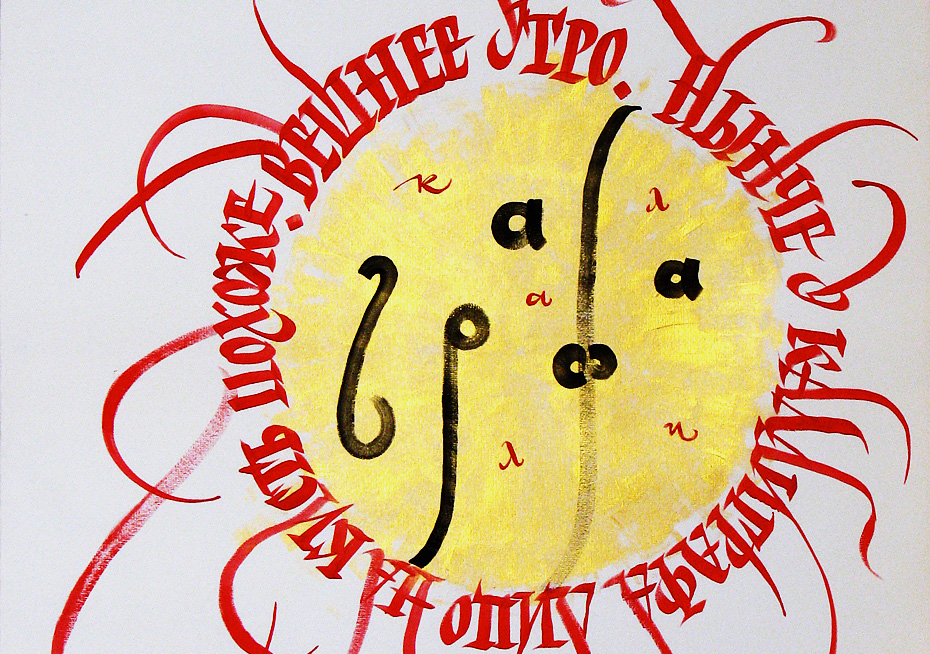
Соло шрифта Amalta
Шрифт Amalta, по­бе­ди­тель Меж­ду­на­род­но­го ти­по­гра­фи­че­ско­го кон­кур­са TDC2 в 2011 го­ду, — не­обыч­ный об­ра­зец пе­ре­осмыс­ле­ния кал­ли­гра­фии в на­бор­ном шриф­те. О про­цес­се ра­бо­ты над про­ек­том рас­ска­зы­ва­ет Ве­ра Ев­стафье­ва, гра­фи­че­ский и шриф­то­вой ди­зай­нер, кал­ли­граф, осно­ва­тель соб­ствен­ной сло­во­лит­ни Infonta. Сре­ди шриф­тов её ав­тор­ства — по­пу­ляр­ный гро­теск Direct, изящ­ная ак­ци­дент­ная Dulsinea, ряд ин­те­рес­ных гар­ни­тур с ис­то­ри­че­ским ис­сле­до­ва­ни­ем в осно­ве. Ве­ра Ев­стафье­ва — ре­гу­ляр­ный участ­ник меж­ду­на­род­ных кон­фе­рен­ций по шриф­ту и ти­по­гра­фи­ке, а в про­шлом пре­по­да­ва­тель Мо­сков­ско­го го­су­дар­ствен­но­го уни­вер­си­те­та пе­ча­ти (Ве­ра за­кон­чи­ла ху­до­же­ствен­ный фа­куль­тет в 2003-м) и Бри­тан­ской выс­шей шко­лы ди­зай­на.
оро­ше­му ар­хи­тек­то­ру до­ста­точ­но ли­ста и ка­ран­да­ша: в бы­стром эс­ки­зе он спо­со­бен пе­ре­дать объ­ё­мы це­ло­го ком­плек­са зда­ний без углуб­ле­ния в де­та­ли. Чи­та­тель, зна­ко­мый со шриф­та­ми Ве­ры Ев­стафье­вой, на­вер­ня­ка со­гла­сит­ся, что без­упреч­ное чув­ство фор­мы — од­на из клю­че­вых черт её сти­ля. Кро­ме то­го, не за­бу­дем про лю­бовь к пи­шу­ще­му ин­стру­мен­ту, хо­тя шриф­ты Ве­ры не сле­по под­чи­ня­ют­ся су­ро­вым за­ко­нам, дик­ту­е­мым ши­ро­ко­ко­неч­ным или остро­ко­неч­ным пе­ром: ру­ко­пис­ная прак­ти­ка ско­рее под­пи­ты­ва­ет ис­ко­мые фор­мы букв. И на­ко­нец, оче­вид­но при­сталь­ное вни­ма­ние к ис­то­рии ки­рил­ли­цы, ко­то­рую Ев­стафье­ва рас­смат­ри­ва­ет не как ис­точ­ник укра­ше­ний «а-ля рюс», но как ключ к есте­ствен­но­му «го­ло­су» тек­ста, на­бран­но­го ки­рил­ли­цей. Всё это мы най­дём и в шриф­те Amalta, и тем лю­бо­пыт­нее услы­шать от са­мо­го ди­зай­не­ра об ис­то­рии его со­зда­ния и глав­ных осо­бен­но­стях.
По­сле окон­ча­ния ху­до­же­ствен­но­го фа­куль­те­та Мо­сков­ско­го го­су­дар­ствен­но­го уни­вер­си­те­та пе­ча­ти в 2003 го­ду Ве­ра Ев­стафье­ва от­пра­ви­лась в Ко­ро­лев­скую ака­де­мию ис­кусств в Га­а­ге и ста­ла пер­вым рос­сий­ским сту­ден­том зна­ме­ни­то­го се­го­дня фа­куль­те­та Type & Media. Про­ра­бо­тав не­сколь­ко лет ди­зай­не­ром шриф­то­во­го от­де­ла Сту­дии Ар­те­мия Ле­бе­де­ва, Ве­ра пе­ре­клю­чи­лась на са­мо­сто­я­тель­ную ра­бо­ту и се­го­дня яв­ля­ет­ся не­за­ви­си­мым ди­зай­не­ром. Моск­ва, 2013. Фо­то: Ксе­ния Плот­ни­ко­ва.
C че­го на­чал­ся шрифт Амаль­та?
Дав­ний опыт учёбы у гол­ланд­ских ди­зай­не­ров (осо­бен­но ана­ли­ти­че­ская кал­ли­гра­фия пе­ром и ки­стью), шриф­то­вой ди­зайн, изу­че­ние и рас­смат­ри­ва­ние раз­но­об­раз­ных ис­то­ри­че­ских ма­те­ри­а­лов и пре­по­да­ва­ние по­мо­гли на­ко­пить мне те зна­ния, мыс­ли и по­бу­жде­ния, ко­то­рые про­яви­лись в Амаль­те.
Не счи­тая сту­ден­че­ских про­ек­тов, Амаль­та — пер­вый не­ком­мер­че­ский шрифт по­сле не­сколь­ких су­гу­бо функ­ци­о­наль­ных ра­бот. Он са­мо­сто­я­тель­но воз­ник из гра­фи­че­ской идеи, и в пер­вую оче­редь я ре­ша­ла эсте­ти­че­скую за­да­чу, оста­вив жёст­кие функ­ци­о­наль­ные тре­бо­ва­ния на вто­ром пла­не — как это и бы­ва­ет при раз­ра­бот­ке боль­шин­ства ак­ци­дент­ных шриф­тов.
Во вре­мя пре­по­да­ва­ния в Бри­тан­ской шко­ле ди­зай­на ме­ня увлек­ло рим­ское ка­пи­таль­ное пись­мо. До это­го я в основ­ном пи­са­ла пе­ром, ко­то­рое лег­че под­даёт­ся кон­тро­лю и жёст­ко опи­ра­ет­ся на бу­ма­гу. Гиб­кость же ки­сти и её сво­бод­ное по­ло­же­ние, па­ре­ние над ли­стом поз­во­ля­ют лег­ко пи­сать штри­хи с вра­ще­ни­ем ли­бо при­ме­нять боль­ший и мень­ший на­жим, слег­ка ме­няя та­ким об­ра­зом тол­щи­ну штри­ха, — и фор­мы ста­но­вят­ся слож­нее, изыс­кан­нее. Как до­ка­зал Эд­вард Ка­тич (ка­то­ли­че­ский свя­щен­ник, кал­ли­граф, пре­по­да­ва­тель, ис­сле­до­ва­тель ран­не­хри­сти­ан­ско­го ис­кус­ства, ав­тор ря­да книг и пуб­ли­ка­ций о пись­ме и рим­ских мо­ну­мен­таль­ных над­пи­сях. — Прим. ред.), имен­но пись­мо ки­стью ле­жит в осно­ве древ­них рим­ских над­пи­сей, вы­се­чен­ных в кам­не, — ки­стью де­ла­ли на­бро­сок, на­ме­ча­ли над­пись.
В ка­кой мо­мент вы по­ня­ли, что от кал­ли­гра­фи­че­ских шту­дий мож­но пе­рей­ти к про­ек­ти­ро­ва­нию на­бор­но­го шриф­та?
Из­ме­няя про­пор­ции и на­сы­щен­ность букв, в про­цес­се ра­бо­ты над не­сколь­ки­ми ком­мер­че­ски­ми над­пи­ся­ми я по­сте­пен­но при­шла к но­во­му по­чер­ку. Сна­ча­ла это бы­ли толь­ко про­пис­ные бук­вы, ко­то­рые «про­рос­ли» саб­ле­вид­ны­ми ро­счер­ка­ми. Этим по­чер­ком я сде­ла­ла над­пись на воз­душ­ном змее, по­том эс­киз для та­ту­и­ров­ки, ещё не­сколь­ко ра­бот и про­сто тре­ни­ро­воч­ные ли­сты. Чем даль­ше, тем яс­нее ста­но­вил­ся ха­рак­тер по­чер­ка и уточ­ня­лись де­та­ли. Поз­же по­яви­лись строч­ные бук­вы по­доб­но­го сти­ля.
При пись­ме с та­ким вы­со­ким кон­трас­том и на­сы­щен­но­стью (стро­ка низ­кая, кисть ши­ро­кая) са­ми со­бой ста­ли воз­ни­кать на­хлё­сты од­но­го штри­ха в бук­ве на дру­гой. Что­бы из­бе­жать не­кра­си­вых и аморф­ных пе­ре­се­че­ний, ру­ка ста­ла по­во­ра­чи­вать кисть и за­острять не­ко­то­рые окон­ча­ния штри­хов. Так сло­жил­ся мой но­вый стиль пись­ма.
Мне ста­ло оче­вид­но, что этот на­ро­жда­ю­щий­ся по­черк со­дер­жит не толь­ко кал­ли­гра­фи­че­ские идеи, но и шриф­то­вые. На­хлё­сты­ва­ю­щи­е­ся друг на дру­га окон­ча­ния штри­хов ста­ли основ­ной гра­фи­че­ской те­мой Амаль­ты. От пе­ре­се­че­ния и срас­та­ния со­сед­них букв, да­ю­щих кра­си­вый, виб­ри­ру­ю­щий эф­фект в кал­ли­гра­фи­че­ском ис­пол­не­нии и пре­вра­ща­ю­щих сло­во в мо­но­лит за счёт по­лу­про­зрач­ной крас­ки или ту­ши, при­шлось от­ка­зать­ся — плот­ное чёр­ное шриф­та име­ет дру­гое ка­че­ство, дру­гую вы­ра­зи­тель­ность и не поз­во­ля­ет пе­ре­дать та­кую плот­ность пись­ма.
Мож­но ли од­но­знач­но клас­си­фи­ци­ро­вать по­лу­чив­ший­ся шрифт?
Амаль­та по­лу­чи­лась со­вре­мен­ным шриф­том гол­ланд­ско­го тол­ка. Сверх­жир­ная ан­ти­ква? Не мо­гу най­ти бо­лее аде­кват­ной ха­рак­те­ри­сти­ки, чем Blackletter — мет­ка, ко­то­рая по­яви­лась вско­ре по­сле пуб­ли­ка­ции Амаль­ты на MyFonts. В рус­ской тер­ми­но­ло­гии точ­но та­ко­го же сло­ва нет, этот тер­мин охва­ты­ва­ет все очень на­сы­щен­ные, тём­ные шриф­ты, в основ­ном го­ти­ку, но тер­мин чуть ши­ре. На­звать Амаль­ту кал­ли­гра­фи­че­ским шриф­том бу­дет не­вер­но. Его осно­ва — пись­мо ки­стью, и эта осно­ва счи­ты­ва­ет­ся в той или иной сте­пе­ни, од­на­ко гар­ни­ту­ра не за­ду­ма­на как за­ме­ни­тель или кон­ку­рент пись­ма, и да­же ро­счер­ки, ре­а­ли­зо­ван­ные как воз­мож­ное, но не­обя­за­тель­ное до­пол­не­ние, не ме­ня­ют её сти­ли­сти­ки и жан­ра. Это ак­тив­ная ак­ци­ден­ция с мощ­ным чёр­ным и вы­ра­зи­тель­ным бе­лым.
То есть Амаль­та не ими­ти­ру­ет пись­мо? Чем всё-та­ки она от­ли­ча­ет­ся от мно­го­чис­лен­ных кал­ли­гра­фи­че­ских де­ко­ра­тив­ных шриф­тов?
Шрифт Amalta на раз­во­ро­те кни­ги Snow White by Brothers Grimm. Ди­зайн и фо­то: Roberto de Vicq de Cumptich. Ил­лю­стра­тор: Camille Rose Garcia.
Нет ли у вас пла­нов раз­вить шрифт? Со­здать до­пол­ни­тель­ные на­чер­та­ния?
В бли­жай­шее вре­мя я не пла­ни­рую рас­ши­рять шрифт, хо­тя у ме­ня по­яв­ля­лось же­ла­ние до­ба­вить на­чер­та­ния для на­бо­ра тек­ста, что сде­ла­ло бы те­пе­реш­нее на­чер­та­ние Амаль­ты за­го­ло­воч­ным.